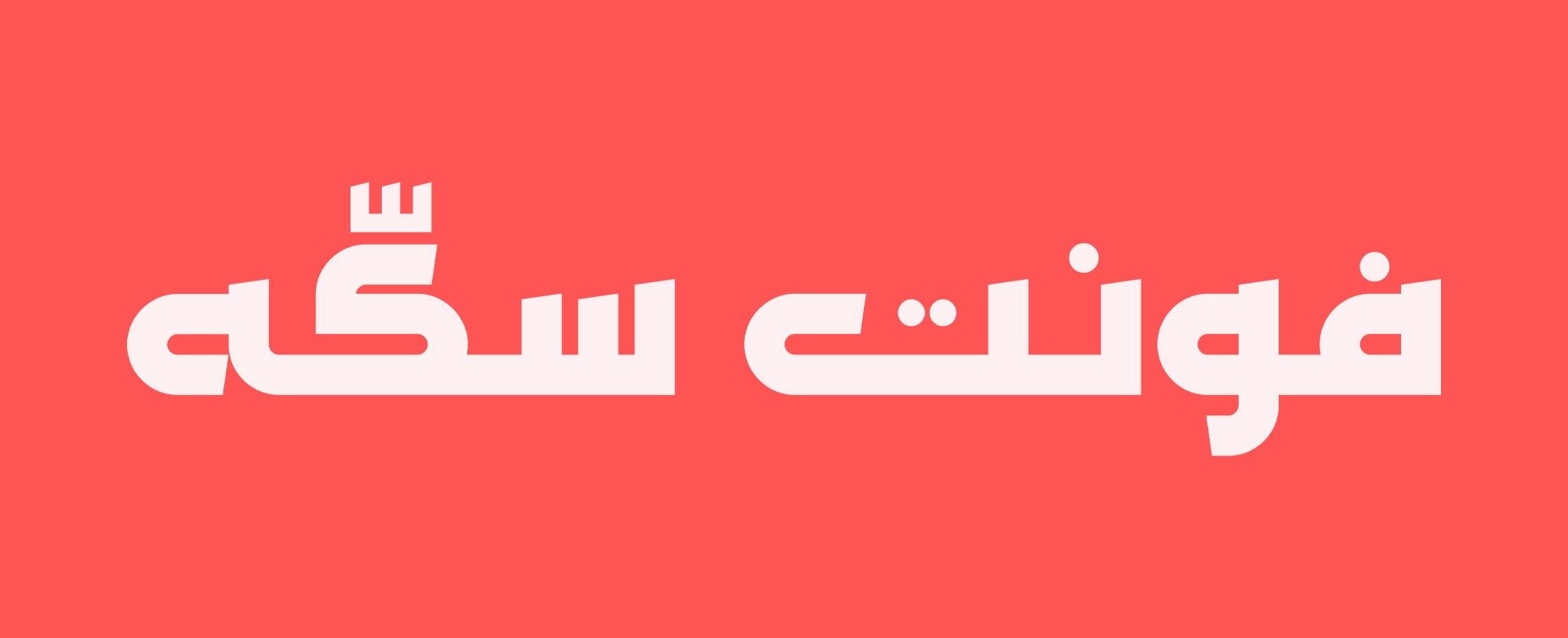
فونت سکه
فونت سکه حاصل نگاهی دوباره به نقش‌ها و خطوط حک شده بر روی سکه‌های تاریخی است؛ جایی که خوشنویسی، هویت و قدرت در دایره‌ای کوچک به نمایش درمی‌آمد. این فونت تلاش می‌کند همان صلابت، نظم هندسی و ماندگاری را به حروف فارسی بیاورد. ساختار زاویه‌دار و تقریبا بنایی آن، یادآور سنت کوفی است؛ اما در عین حال با بیانی تازه و معاصر بازآفرینی شده است.
این فونت برای تیترها و عنوان‌های شاخص طراحی شده است؛ جایی که نیاز به حضوری قاطع و ماندگار داریم. سکه ساده است اما غریب نیست، آشناست اما تکراری نه؛ بازتابی از تاریخ که با زبان امروز سخن می‌گوید.
فونت سکه خروجی پروژه پایان‌نامه کارشناسی ارشد است که با راهنمایی دکتر صداقت جباری شکل گرفته. این فونت با الهام از ساختار هندسی خطوط کوفی روی یکی از سکه‌های تاریخی طراحی شده و هویتی قدرتمند، قاطع و در عین حال مدرن دارد.
فونت سکه در دو وزن Fat و Black  ارائه می‌شود و به‌طور ویژه برای تیترها و عنوان‌های شاخص طراحی شده است. ترکیب زوایای هندسی با سطوح نرم و یکپارچه، آن را برای کاربردهای گرافیکی، پوستر، جلد کتاب، برندینگ و پروژه‌های فرهنگی-هنری بسیار مناسب می‌سازد
فونت سکه با تمرکز بر ساختار هندسی و قاطع کوفی طراحی شده و در روند طراحی آن، اصول زیر مورد توجه قرار گرفته است:
1. لیگچرها و ترکیبات ویژه: برخی ترکیب‌های پرکاربرد حروف به‌صورت اختصاصی طراحی شده‌اند تا علاوه بر زیبایی‌شناسی، جریان بصری متن روان‌تر شود.
2. تناسبات هندسی حروف: فرم‌ها بر پایه‌ی دایره، مربع و خطوط مستقیم ساخته شده‌اند تا هارمونی بصری در کل فونت ایجاد شود.
3. چشم حروف و فضاهای داخلی: در طراحی فونت، تعادل میان چشم حروف و ضخامت بدنه به‌گونه‌ای رعایت شده که خوانایی و قدرت بصری حفظ شود.
4. هماهنگی برش‌ها و پایان خطوط: انتهای حروف دارای برش‌های یکدست و هماهنگ است تا هویت فونت منسجم باقی بماند.
فونت سکه علاوه بر فارسی، از عربی، اردو، کردی و انگلیسی نیز پشتیبانی می‌کند. این تنوع باعث می‌شود فونت سکه گزینه‌ای مناسب برای پروژه‌های چندزبانه باشد